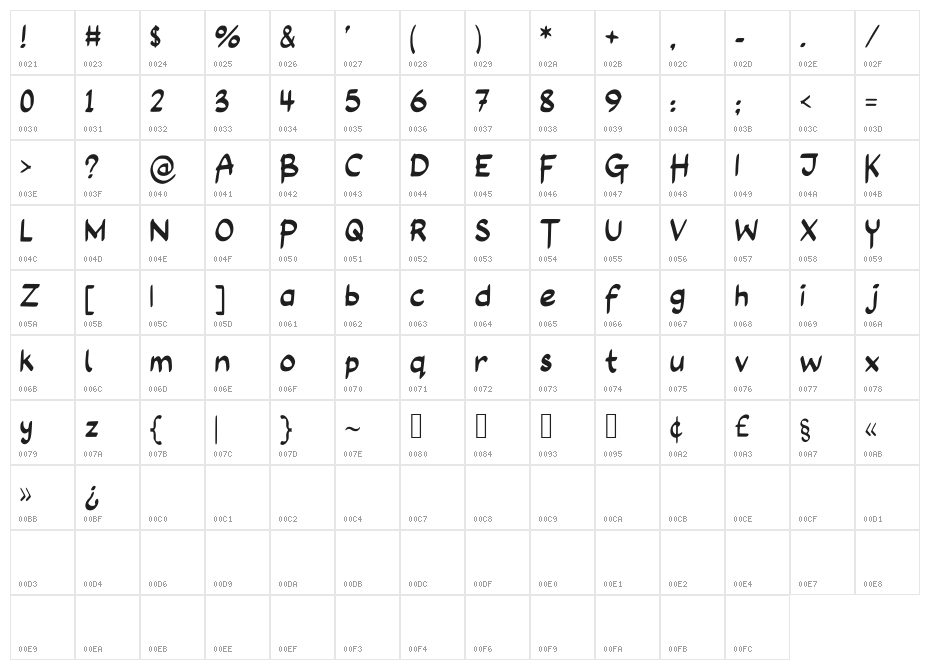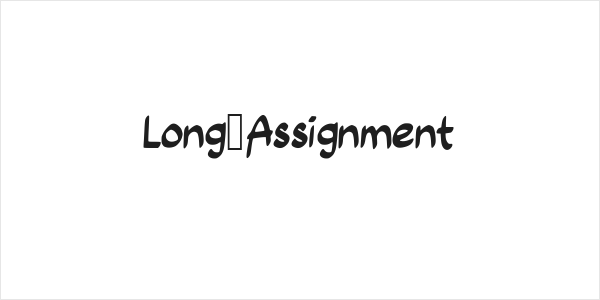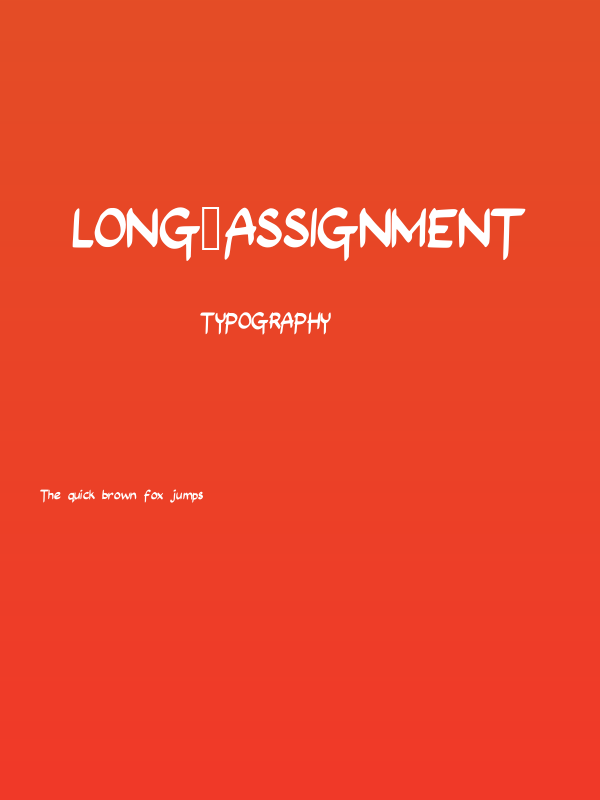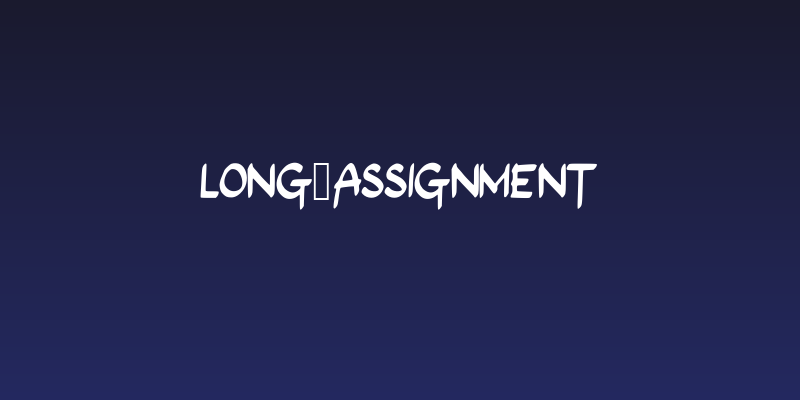
Long_Assignment Font
| Gesamtstil | Playful, Energetic |
| Vorgeschlagene Projekte | Ideal for children's books, playful branding, casual invitations, and creative posters. |